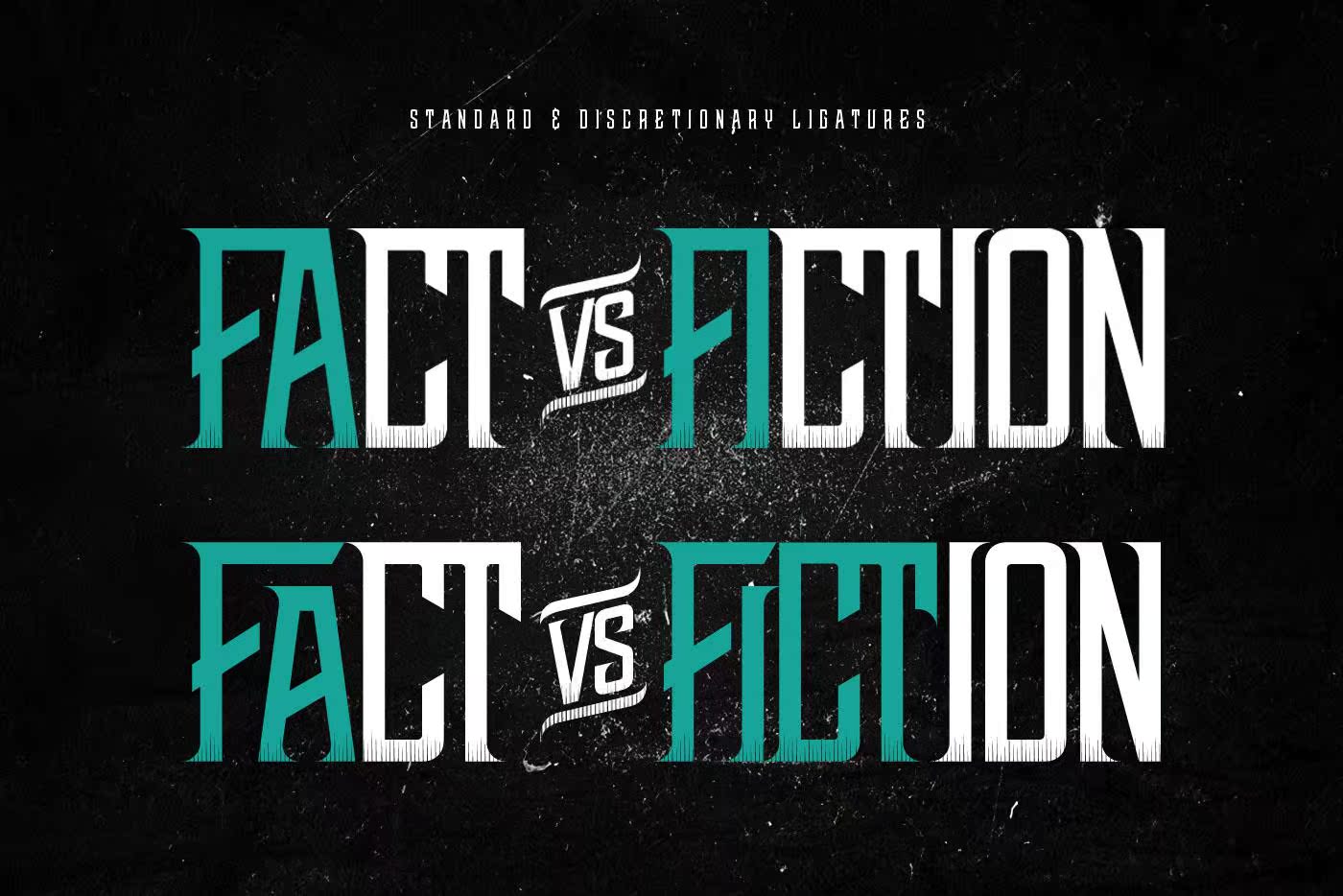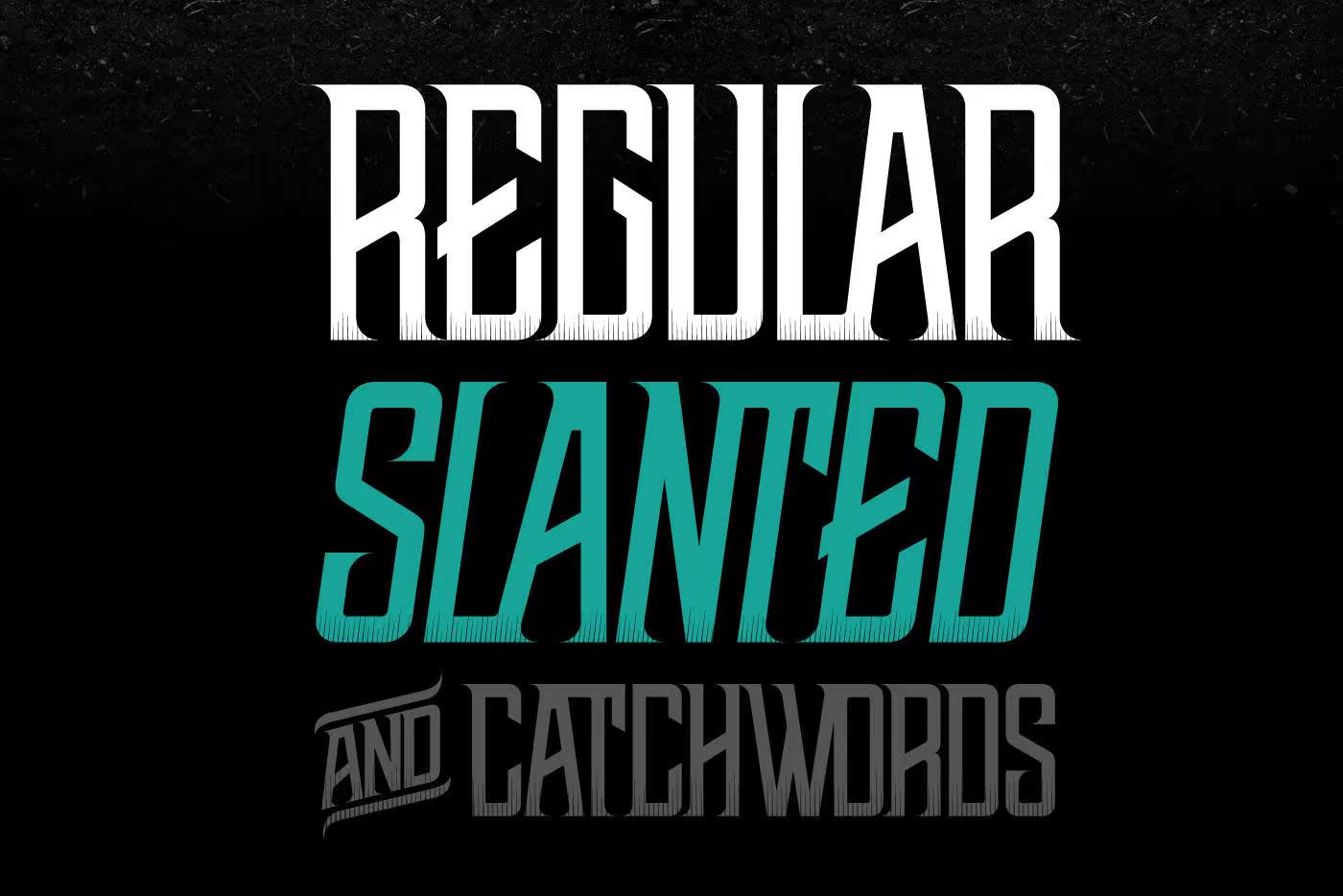
FreeNWBMarvisdisplay是我们今天可以拥有的一种基本字体。这种字体是一种具有暂时感觉的字体。19世纪晚期,Spiredits的设计具有美学意义,但它同样适用于现代设计应用。因此,它可以使用最新的字体和更完整的字体设置和样式。Goggetting PremiumVersion,它的特点是有290个连字,1357其作品的总体字形、上下文。此外,它还与辅助替代词和35+流行语相结合。这些功能适用于Posterheadline、Movietitle、productlabels和BrandIdentity的深入排版自定义选项。